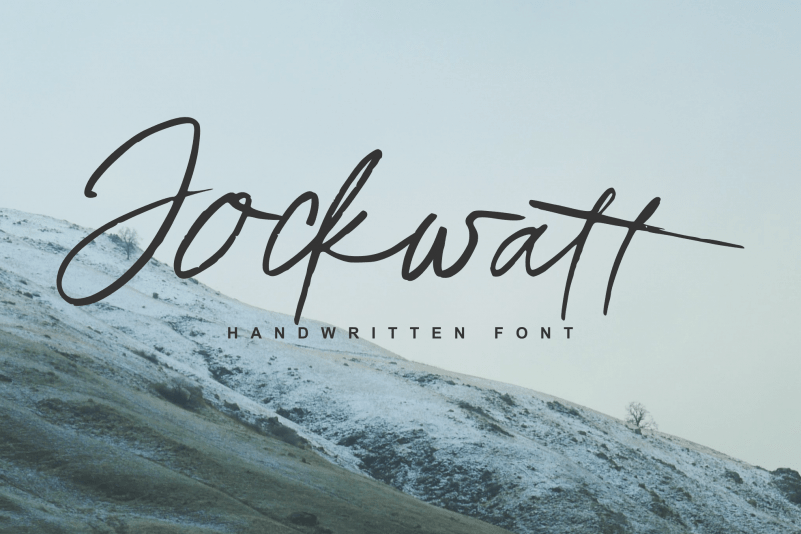
Jockwatt Script Font – Download Grátis
A fonte Jockwatt Script é uma escolha perfeita para quem busca estilizar seu design com a modernidade do calligrafia. Perfeitamente projetada para aplicativos como marca de produtos, convites de casamento ou cartões personalizados, esta fonte está repleta de elementos necessários para tornar seu projeto impecável. Jockwatt oferece um conjunto completo de letras maiúsculas e minúsculas, números, vários sinais de pontuação e uma rica coleção de ligação de caracteres. Essa combinação de elementos faz com que sua fonte seja a escolha ideal para dar vida ao seu design, tornando-o mais único e atraente. Seja em um convite de casamento ou até mesmo no pacote da sua marca, Jockwatt mantém o estilo moderno do calligrafia, transformando suas ideias em textos que chamam atenção.